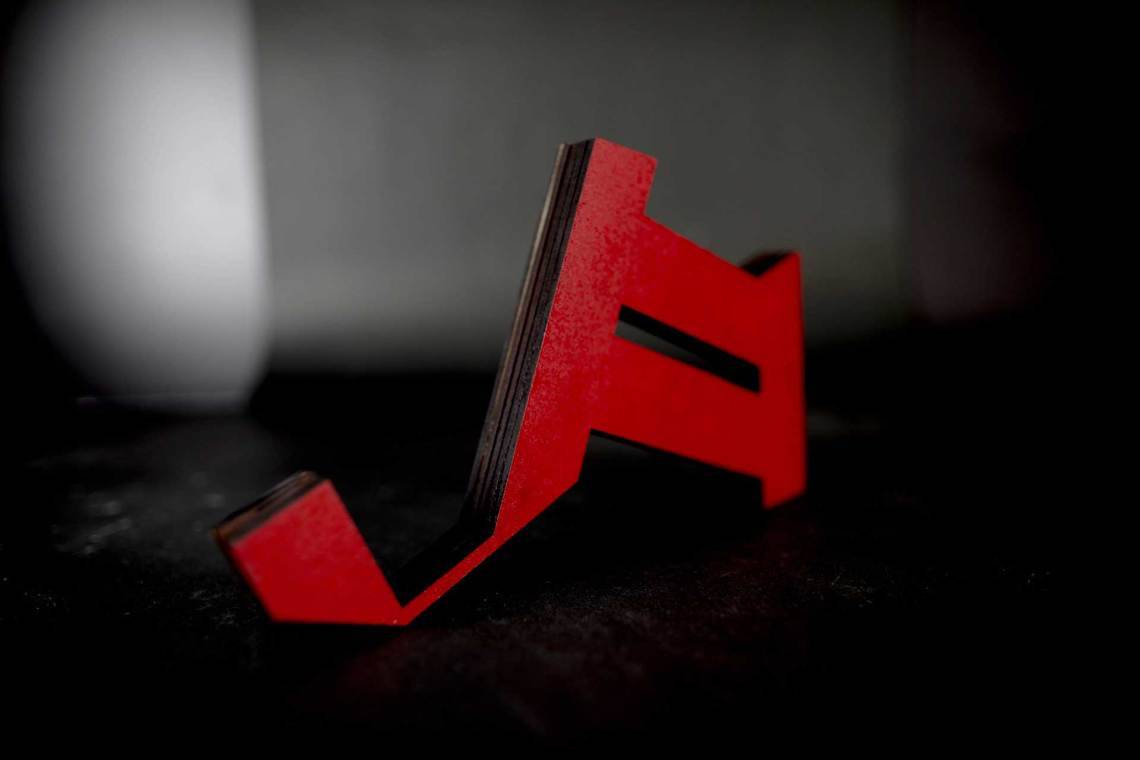
فونت فارسی و عربی LT Azal پایه کوفی
فونت فارسی و عربی کوفی 29LT Azal یک فونت عربی دارای گژپچ است که در ایران فونت برای کاربران خوب ایرانی معرفی میشود. امیدواریم از تایپ با آن لذت ببرید. و همچنین برای شما عزیزان پرکاربرد و مفید باشد.
فونت فارسی و عربی LT Azal پایه کوفی یک فونت هندسی معاصر عربی است ، این فونت برای صفحه نمایش با ویژگی قطر بالا و ظرافت در خط نازک و زیبایی منحصر به فردی توسط دانشجویان CAAD Students  در سال 2017 طراحی شده است
ساختار فونت حاشیه ضخیم و لبه های تیز است که با نقاط دایره ای متضاد است
در کجا میتوان از این فونت استفاده کرد؟